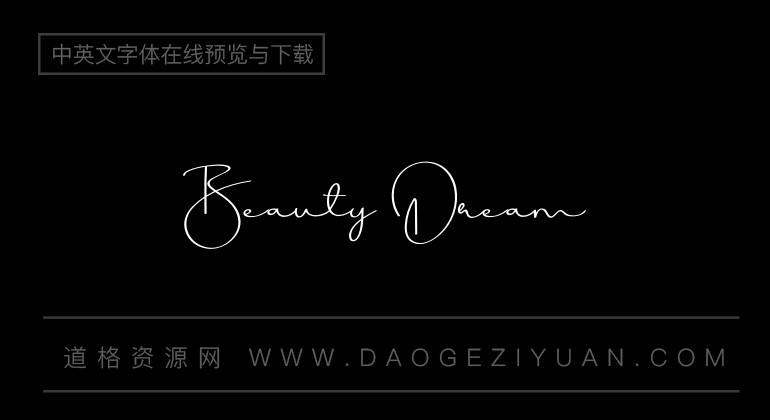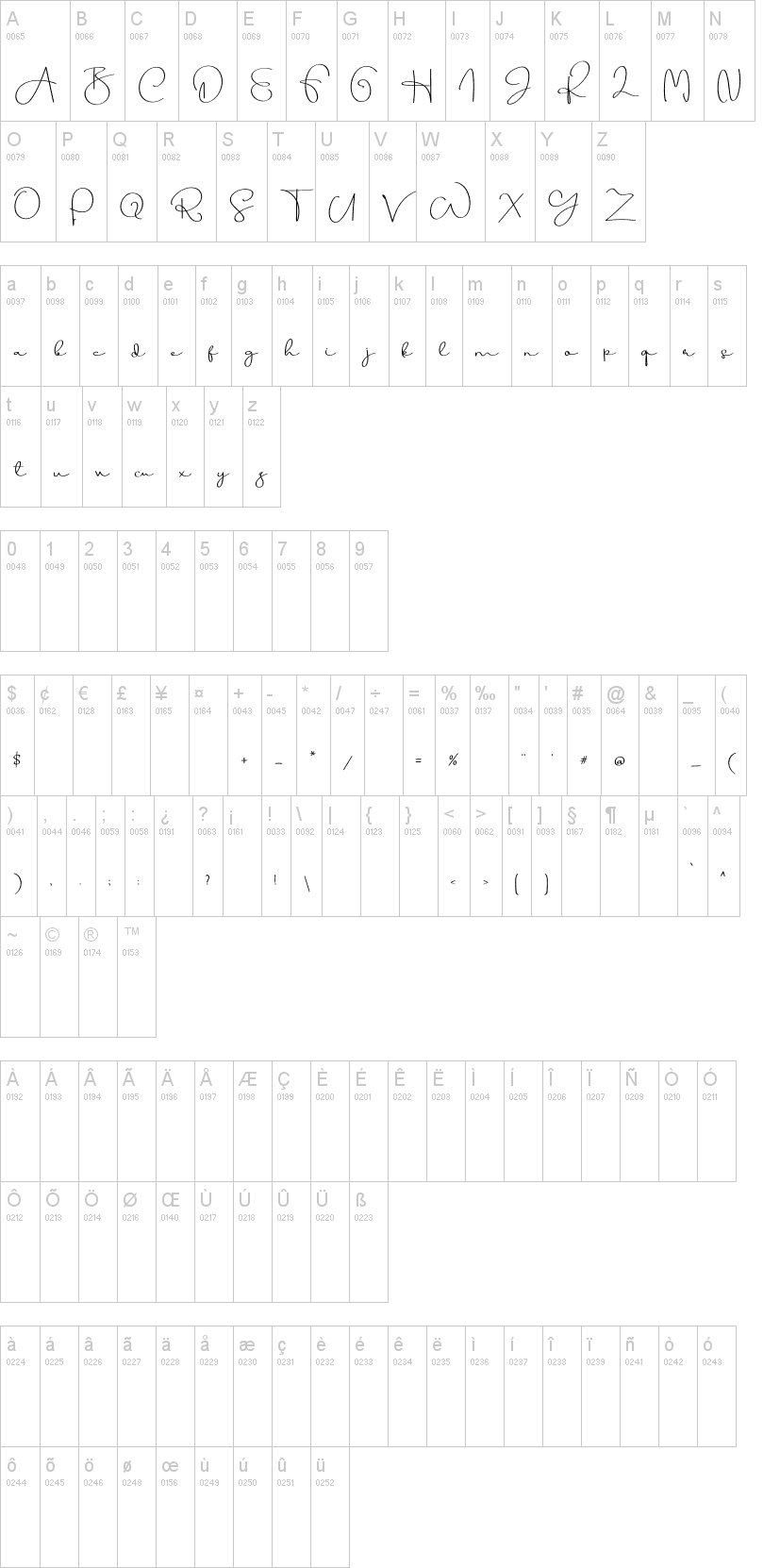
Beauty Dream是一种美丽的手写风格字体,其字母和符号都带有自然而优美的笔画。这种字体整体上看起来非常柔和,有着流畅而优雅的曲线,适合用于漂亮而优雅的设计项目,比如婚礼邀请函、手写风格海报、漂亮的标志等等。该字体有多种字重和变体可供选择,可以在不同的设计场景中灵活运用。内容介绍
Beauty Dream是一款非常不错的手写艺术字体,具有很好的视觉感,适合于文化类的宣传设计、商业类品牌的广告和产品包装设计以及个性化文字排版等较多场景。